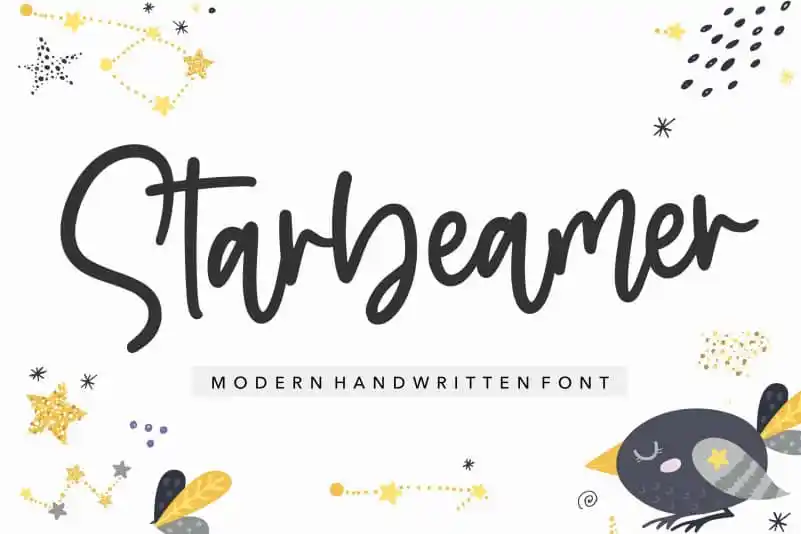
Starbeamer Modern Handwritten font – Download Grátis
A Starbeamer Modern Handwritten é uma fonte que se destaca por sua personalidade única e encantadora. Perfeita para designers buscando adicionar um toque especial a seus projetos, esta fonte é ideal para aplicações como embalagens de produtos, projetos de marca, revistas, redes sociais, casamentos ou simplesmente quando você quer destacar as palavras sobre o fundo. Com sua escrita elaborada e emotiva, Starbeamer Modern Handwritten oferece uma expressão visual rica e envolvente. Suas linhas curvas fluidas e detalhes sutis criam um design gráfico que é atraente para qualquer aplicação, seja ela em comunicados de marketing, designs de produto ou criações digitais. Além do seu charme, a Starbeamer Modern Handwritten também se destaca pela sua facilidade de uso. Perfeitamente adaptada para diferentes tamanhos e contextos, esta fonte manterá uma consistência elegante em qualquer projeto que você decida empregar. Ideal para quem busca expressar nuances emocionais ou estilos distintos através de suas criações visuais.